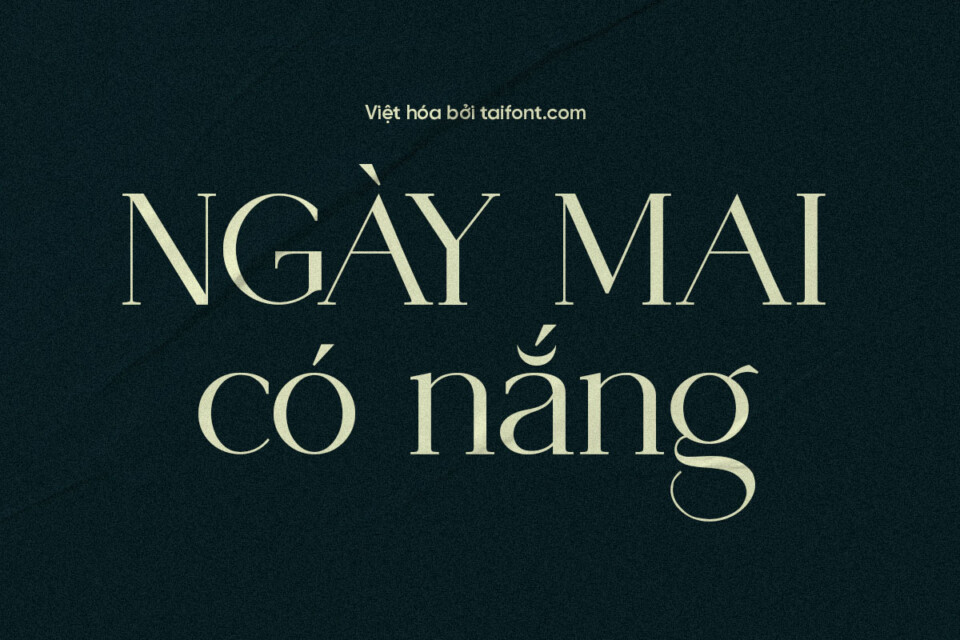
Font 1FTV VIP Vendya Việt Hóa – Font Có Chân Thanh Mảnh Sang Trọng
Font 1FTV VIP Vendya Việt Hóa – Font Có Chân Thanh Mảnh Sang Trọng Cho Thiết Kế Việt
Giới thiệu về Font 1FTV VIP Vendya Việt Hóa – Font Có Chân Thanh Mảnh Sang Trọng
Trong thế giới thiết kế đồ họa hiện đại, việc lựa chọn một bộ Font Miễn Phí chất lượng luôn là ưu tiên hàng đầu của các nhà sáng tạo. Đặc biệt, bộ Font 1FTV VIP Vendya Việt Hóa – Font Có Chân Thanh Mảnh Sang Trọng đã nhanh chóng trở thành tâm điểm chú ý nhờ sự kết hợp hoàn hảo giữa nét cổ điển và hơi thở đương đại. Đây là một phông chữ Serif (có chân) mang phong cách tinh tế, giúp các ấn phẩm truyền thông trở nên chuyên nghiệp và đẳng cấp hơn bao giờ hết. Việc được Việt hóa trọn vẹn giúp người dùng tại Việt Nam dễ dàng sử dụng trong các dự án đòi hỏi tính thẩm mỹ cao mà không lo lỗi font hay thiếu dấu tiếng Việt.
Đặc điểm nổi bật của Font 1FTV VIP Vendya
Điểm thu hút nhất của bộ font này chính là đường nét thanh mảnh nhưng vô cùng sắc sảo. Các nét thanh (hairline) và nét đậm (stem) được tính toán tỉ mỉ, tạo nên sự cân bằng thị giác tuyệt vời. Kiểu dáng của nó gợi lên sự thanh lịch, quý phái, rất phù hợp cho những thương hiệu thời trang, mỹ phẩm hoặc các thiệp mời sự kiện cao cấp. Ngoài ra, bộ ký tự đi kèm cũng rất phong phú, hỗ trợ tối đa cho việc trình bày văn bản sáng tạo.
Ứng dụng thực tế của Font 1FTV VIP Vendya Việt Hóa – Font Có Chân Thanh Mảnh Sang Trọng
Nhờ vẻ ngoài cuốn hút, bộ font này được ứng dụng rộng rãi trong nhiều lĩnh vực khác nhau, từ in ấn đến hiển thị kỹ thuật số. Dưới đây là những cách bạn có thể tận dụng tối đa sức mạnh của nó:
Thiết kế nhận diện thương hiệu và Logo
Sử dụng Font 1FTV VIP Vendya Việt Hóa – Font Có Chân Thanh Mảnh Sang Trọng trong việc thiết kế Logo sẽ giúp thương hiệu của bạn toát lên vẻ sang trọng và uy tín. Đối với các cửa hàng thời trang cao cấp hoặc các spa làm đẹp, phông chữ này chính là chìa khóa để tạo dấu ấn riêng biệt trong lòng khách hàng. Những đường chân nhọn và gọn gàng giúp tên thương hiệu trở nên dễ nhớ và đầy tính nghệ thuật.
Trình bày tiêu đề sách và tạp chí
Trong lĩnh vực xuất bản, các biên tập viên thường ưu tiên sử dụng font có chân cho các tiêu đề lớn hoặc bìa sách để tạo sự dẫn dắt thị giác tốt hơn. Kiểu chữ Vendya mang lại cảm giác tri thức và cổ điển, rất thích hợp cho những cuốn tiểu thuyết lãng mạn, tập thơ hoặc các tạp chí phong cách sống. Khi kết hợp với các khoảng trắng hợp lý, phông chữ này sẽ tạo ra một bố cục trang nhã và thoáng đãng.
Sáng tạo nội dung trên mạng xã hội
Với sự phát triển của Canva hay Adobe Express, việc tự thiết kế hình ảnh đăng Facebook, Instagram đã trở nên phổ biến. Sử dụng phông chữ Việt hóa này cho các câu trích dẫn (quotes) hoặc ảnh bìa sẽ giúp bài đăng của bạn trở nên nổi bật và thu hút nhiều lượt tương tác hơn từ cộng đồng mạng.
Lưu ý khi sử dụng Font 1FTV VIP Vendya Việt Hóa
Mặc dù là một phông chữ đẹp, nhưng để đạt được hiệu quả tốt nhất, bạn cần chú ý đến một số yếu tố kỹ thuật. Thứ nhất là kích thước chữ: do có những nét rất mảnh, bạn không nên để kích thước quá nhỏ khi in ấn trên các chất liệu nhám hoặc giấy thấm mực để tránh bị mất nét. Thứ hai là sự phối hợp màu sắc: hãy ưu tiên các tông màu tương phản mạnh như chữ vàng đồng trên nền đen hoặc chữ đen trên nền trắng sữa để làm nổi bật sự sang trọng.
Kết luận về bộ font sang trọng này